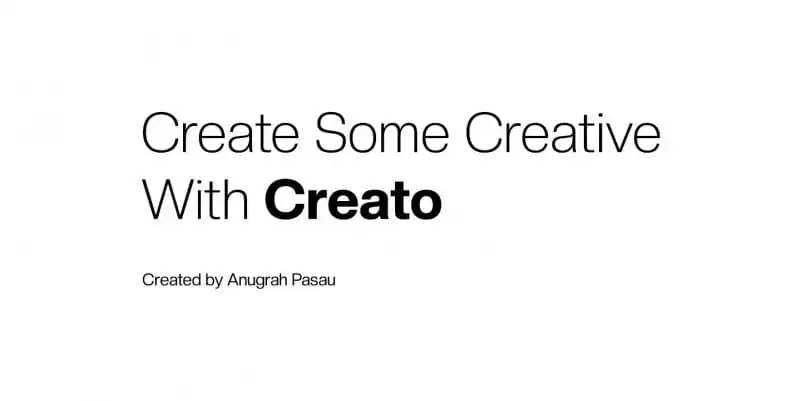
A fonte “Creato Font Family” é uma seleção perfeita para quem busca uma tipografia moderna com toque geométrico. Ela oferece um ar limpo e minimalista, exibindo elegância e charme quixotesco sem deixar de ser versátil ou fácil de ler. Seu design se destaca tanto para uso em gráficos quanto para aplicações visuais como sinais urbanos ou editoriais. “Creato Font Family” é perfeitamente adaptável para diferentes ambientes, fazendo dela uma escolha conveniente para qualquer tipo de aplicação visual, seja ela web, publicitária ou corporativa. Com seu estilo moderno e geométrico, ela certamente se torna um aliado ideal no arsenal de ferramentas digitais para designers gráficos em busca de uma fonte perfeita para atingir o público.